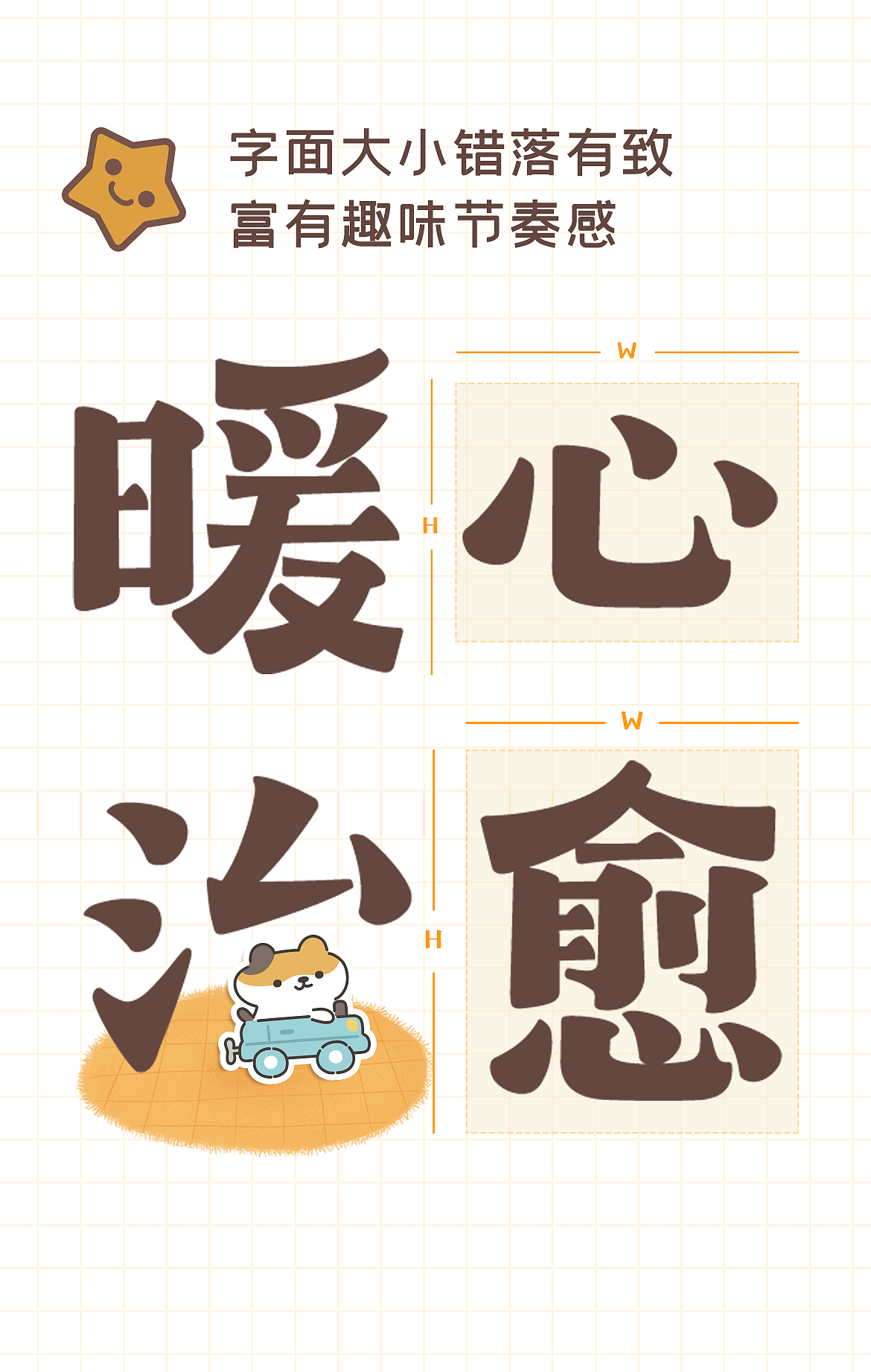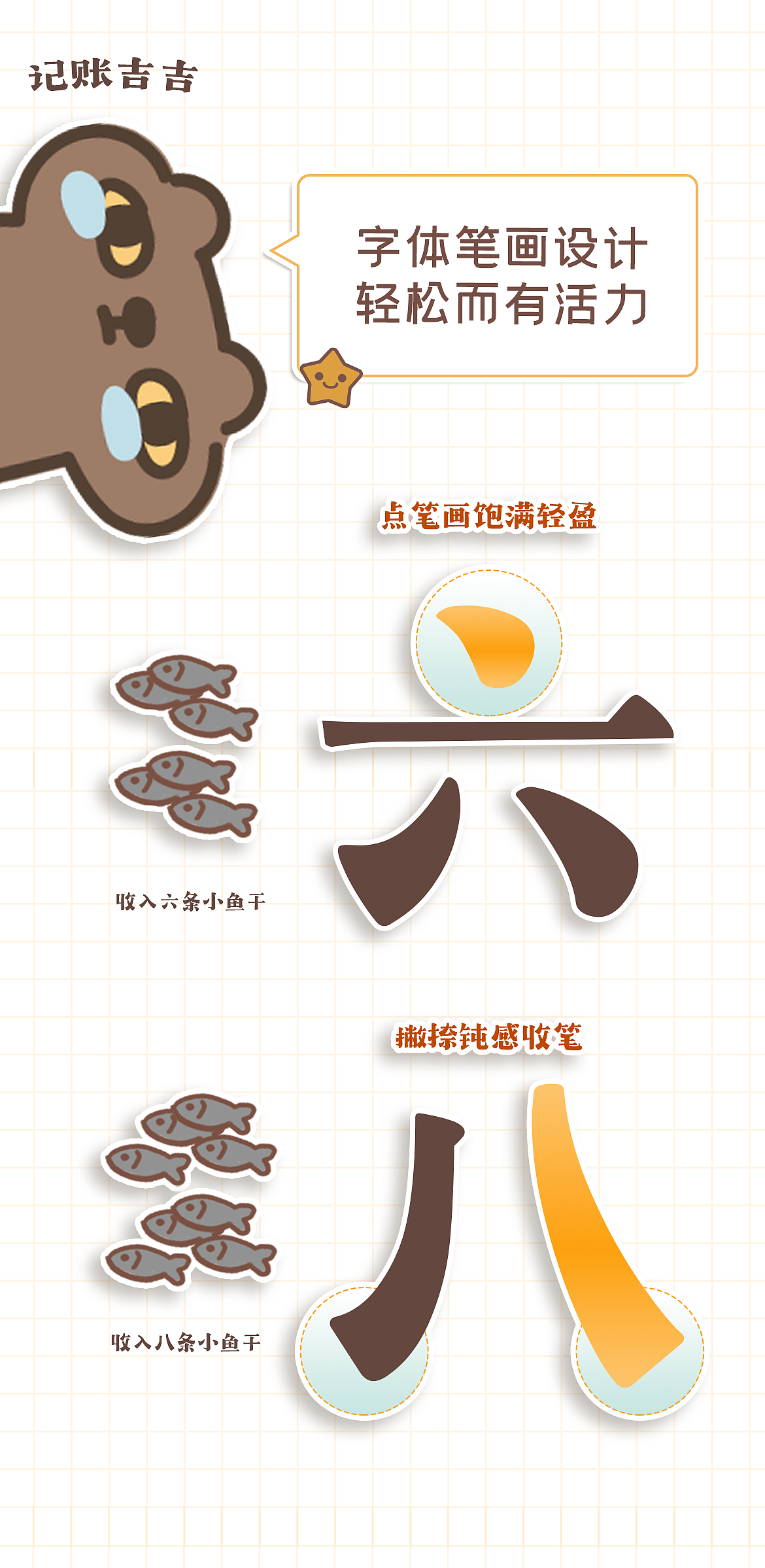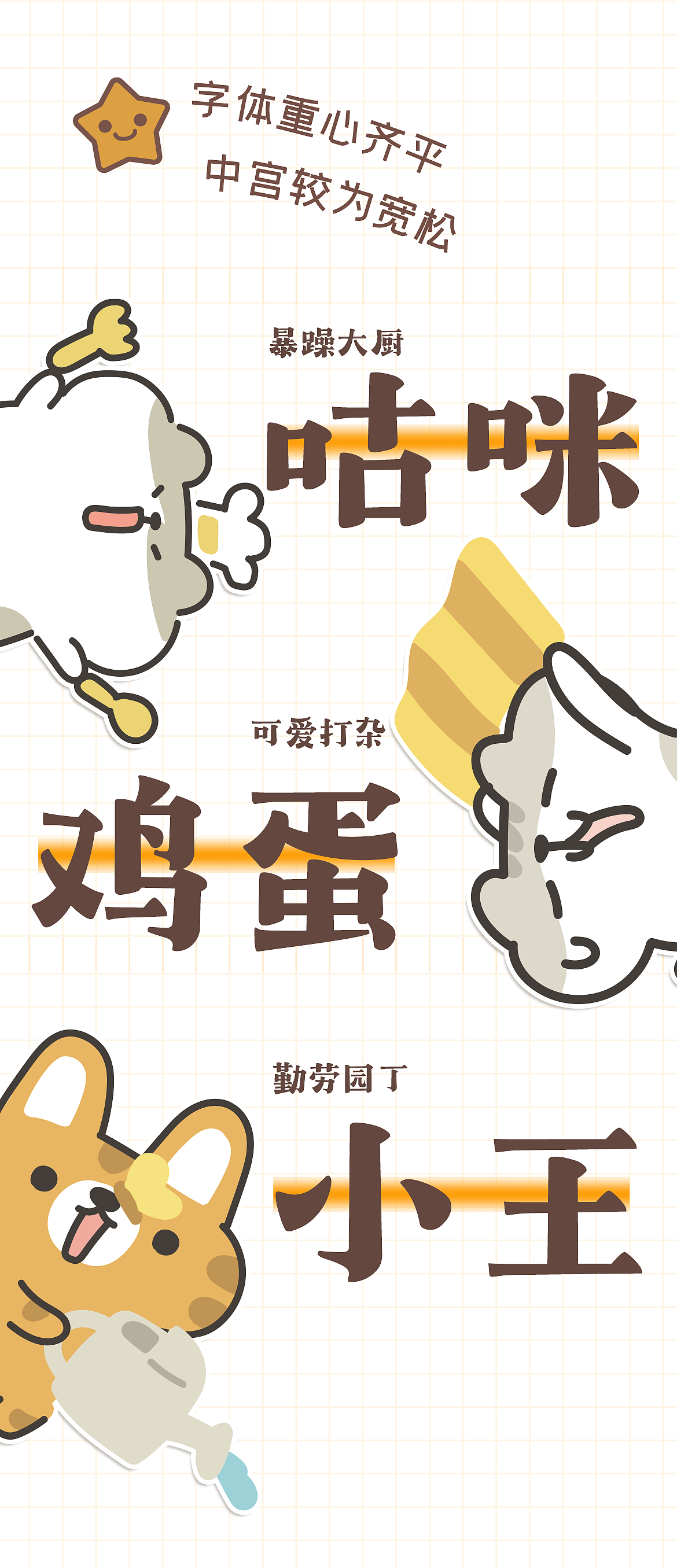
动物IP可爱卡通插画,手游字体设计 | 字魂动物餐厅体
「字魂动物餐厅体」是字魂网和手游动物餐厅的联名字体,也是动物餐厅在游戏之外为所有玩家和伙伴提供的温柔精神归处。
以动物餐厅 角色形象、游戏理念为设计灵感,切入理想中温馨、治愈的世界。字体形象轻盈、舒适、可爱,陪伴在每一位伙伴的日常生活中,让小伙伴们的前行路上有爱伴行。
这是一款卡通感的宋体。字体字面大小错落有致,以宋体为原型,并加以圆润方向的调整,让字形在活泼的风格上多了一份细腻文艺的气质。点笔划饱满而轻盈,撇捺笔划收笔有钝感,视觉效果轻松又不乏活力。